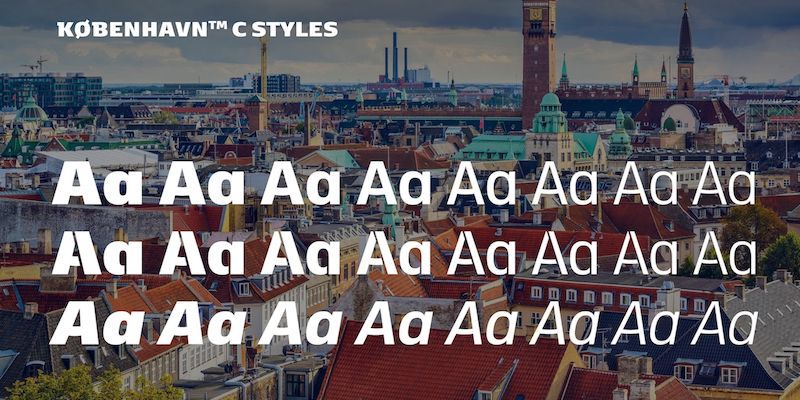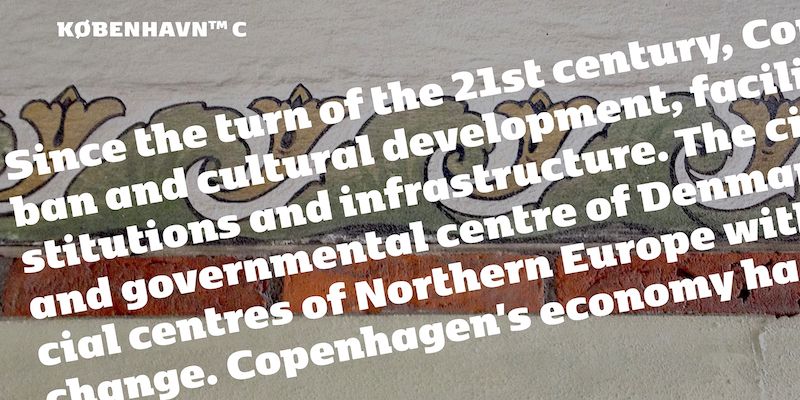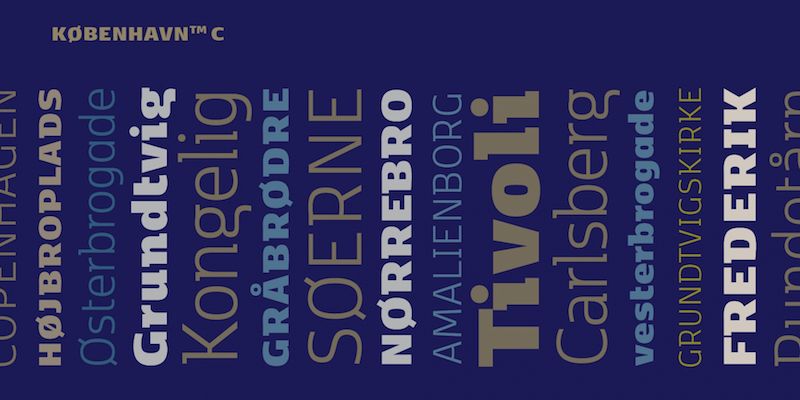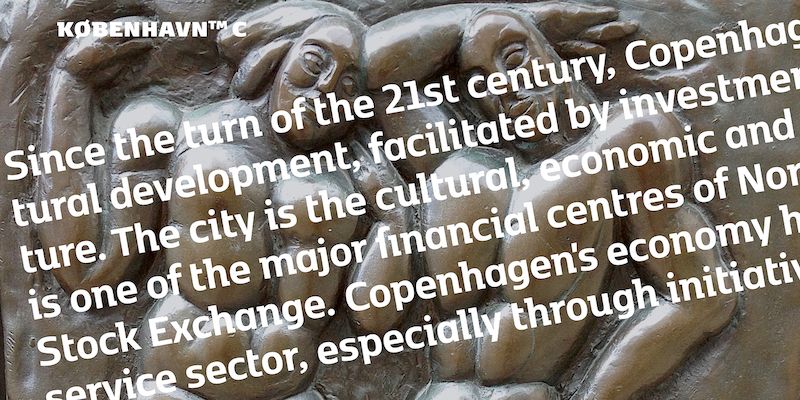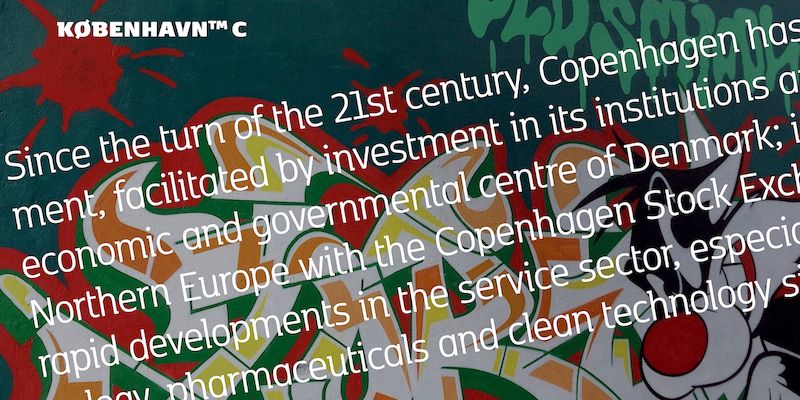
C gehört zur größeren Kobenhavn-Schriftfamilie und ist die Abkürzung für „Condensed“.
Die dänische Hauptstadt Kopenhagen benötigte eine Schrift, die die vielen Facetten der Stadt vereint.
Kultur und visuelle Umgebung der Stadt sowie dänisches Design des 20. Jahrhunderts waren Inspiration für die Form der Buchstaben.
Die Schrift ist verhältnismäßig flach und breit wie die Stadt selbst und weist abgerundete Ecken auf, die eine warme visuelle Stimmung vermitteln. „Beispiele für die Verwendung einer Schrift mit dem gleichen Ziel finden Sie in anderen Teilen der Welt, zum Beispiel zum Kennzeichnen von Ortsbereichen und in Materialen für den Städtetourismus. FP København ist unsere Interpretation einer solchen Schrift“, so die Designer.
Morten Rostgaard Olsen (geboren 1964) ist Grafikdesigner und Schriftenarchitekt und lebt und arbeitet in Kopenhagen. Nach einem fünfjährigen Studium an der dänischen Hochschule für Kunst und Design leitet er jetzt ein Designstudio, in dem er Lösungen für Unternehmensdesigns und -schriften bereitstellt. Er ist außerdem als Dozent und Berater tätig. Zu seinen Kunden gehört das dänische Bildungsministerium in Kopenhagen, das als Erstes seine Schrift FF Olsen einsetzte.